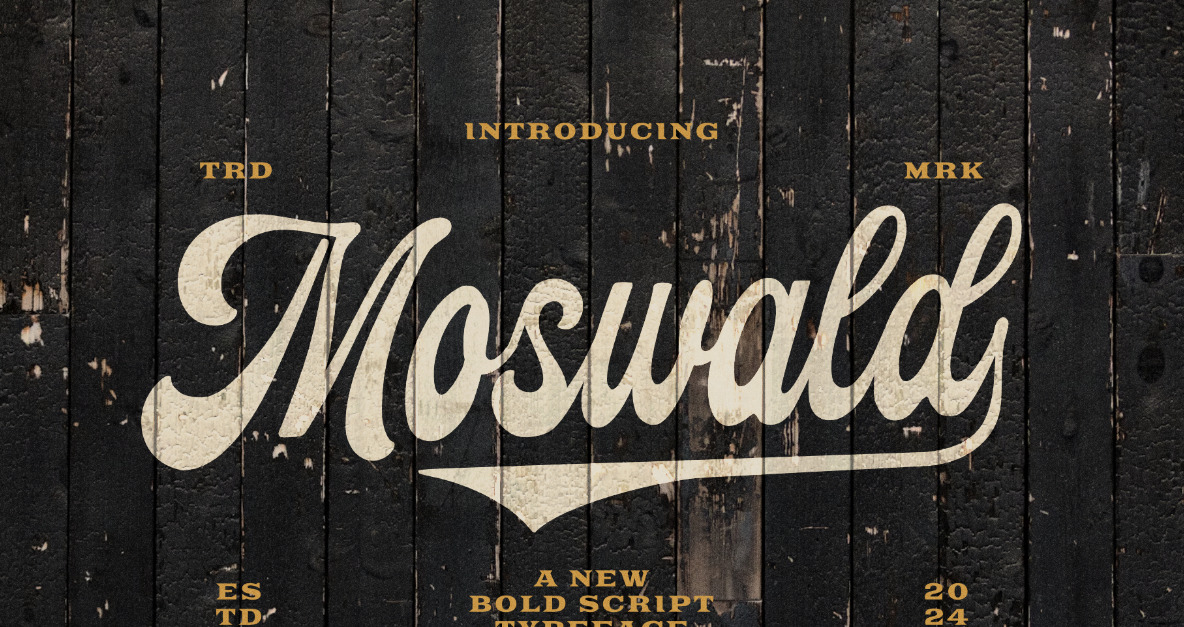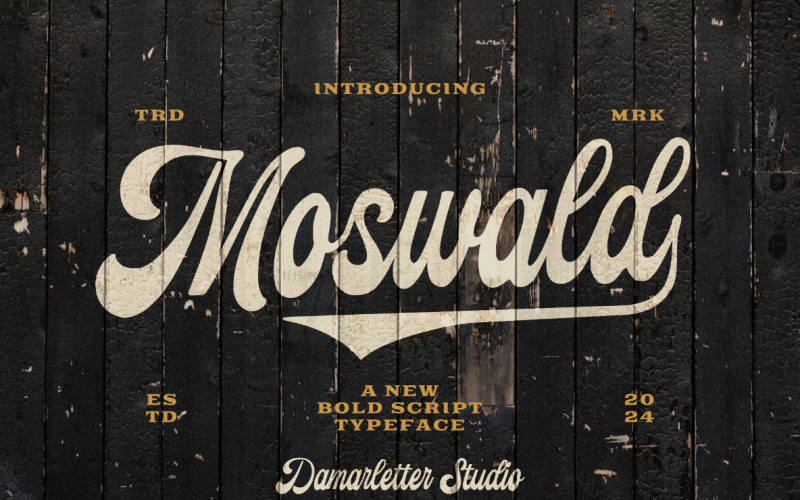
Carattere tipografico dello script scritto a mano da Moswald
Carattere tipografico dello script scritto a mano da Moswald - Caratteristiche Immagine 1